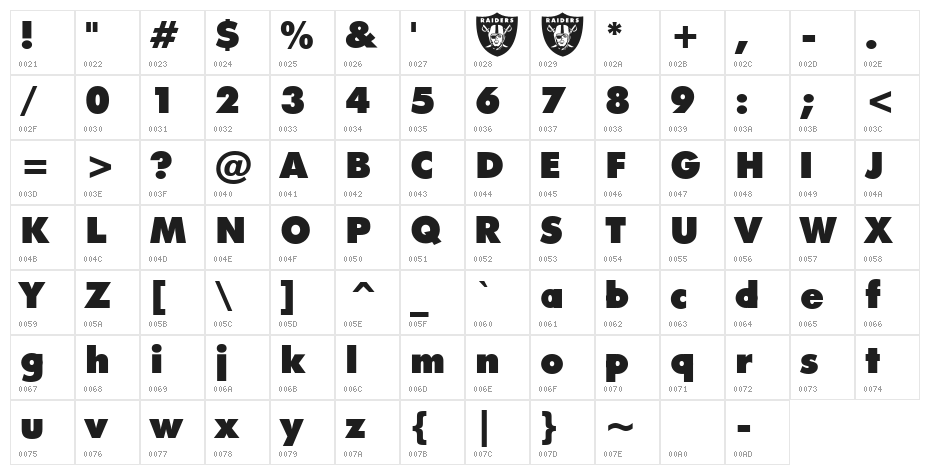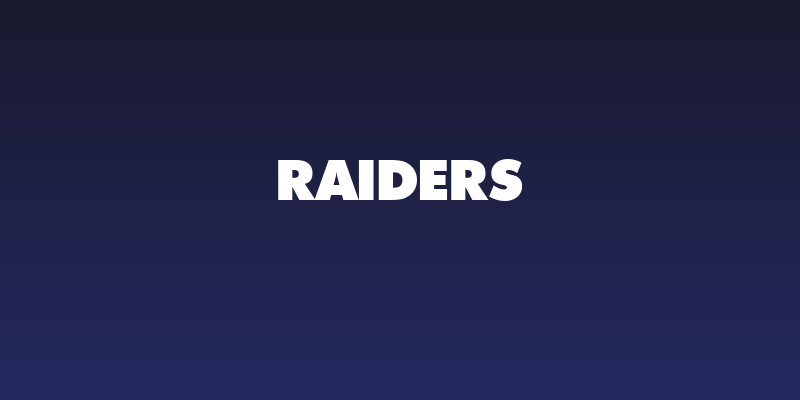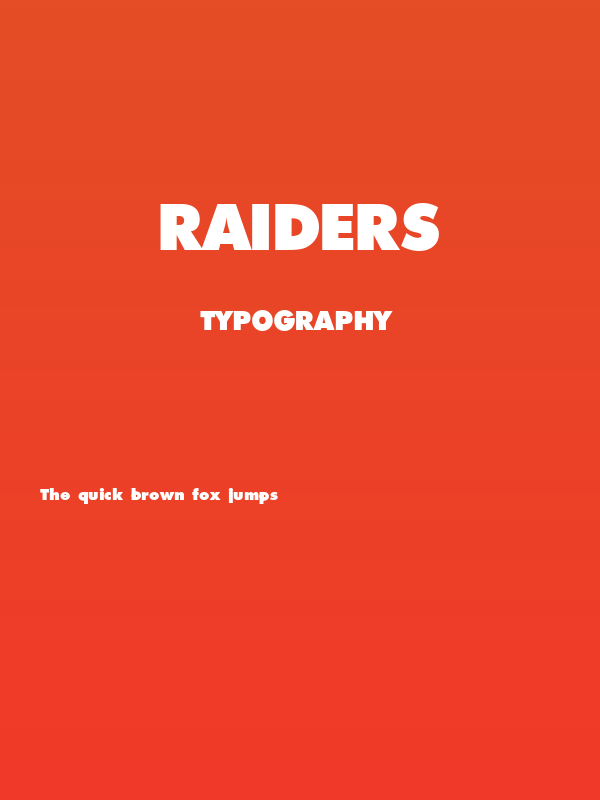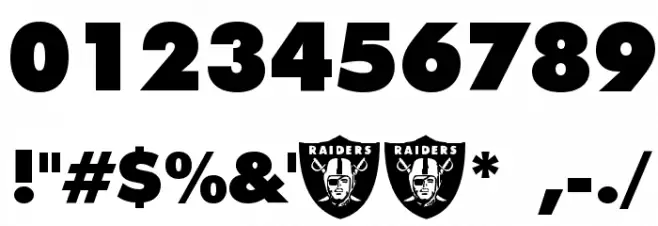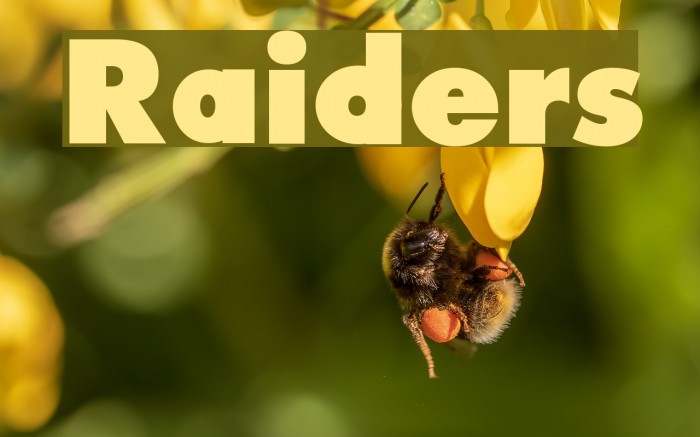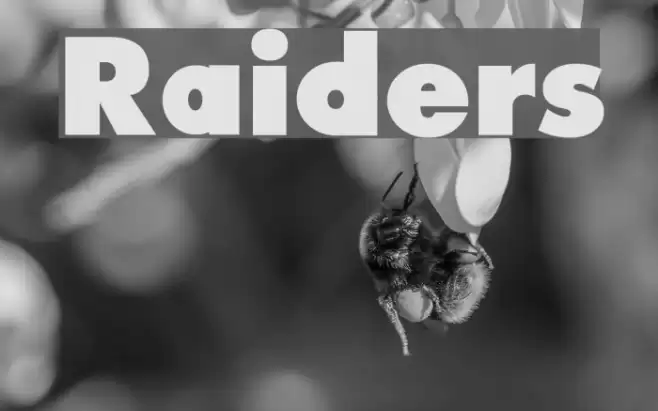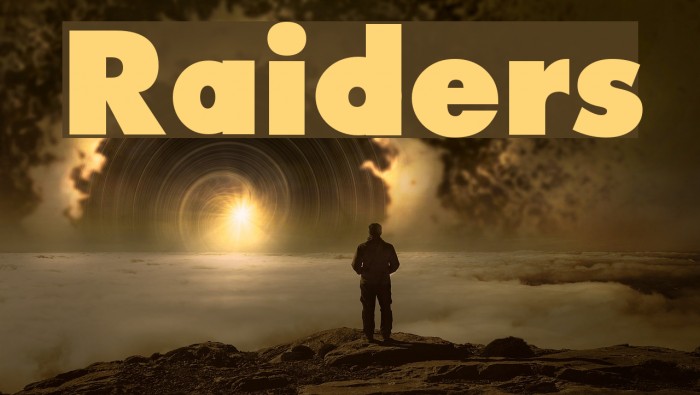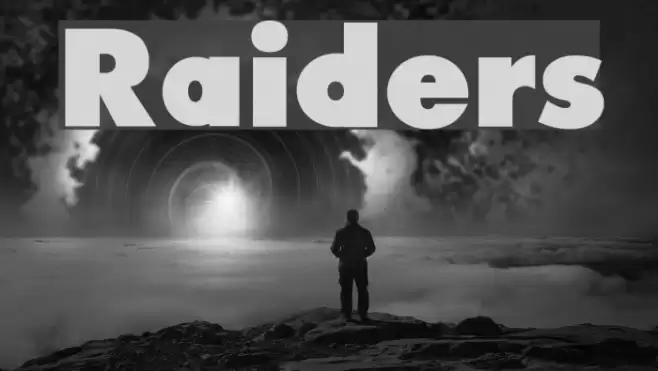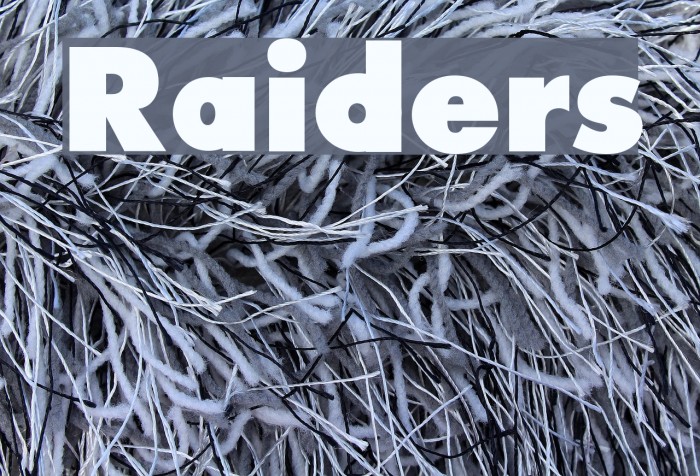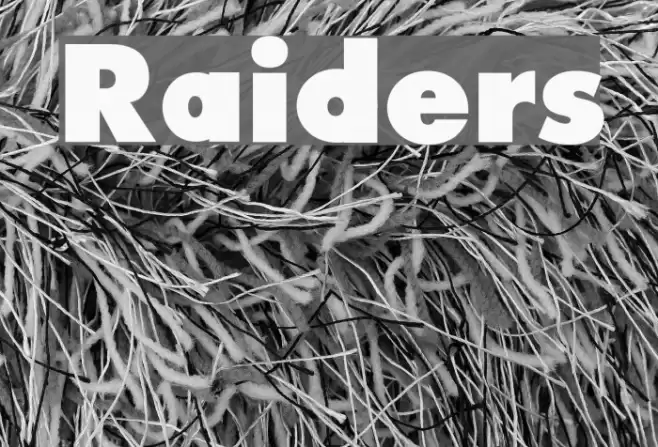
Raiders Font
Fonts by Dennis Ludlow - Sharkshock
| Progetti proposti | Ideal for sports branding, posters, headlines, and logos that require a bold statement. |